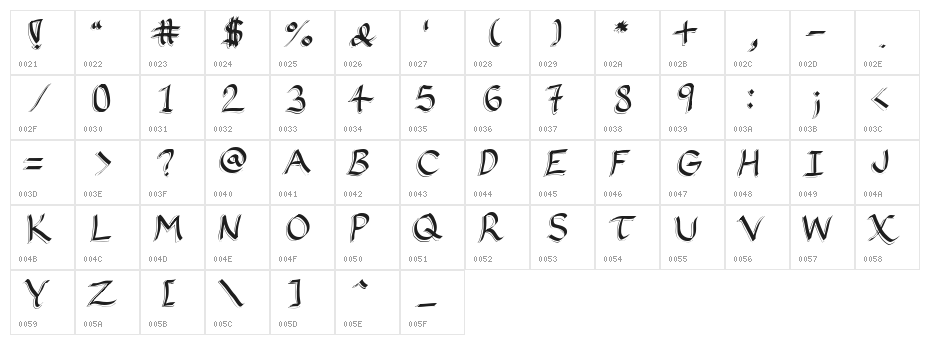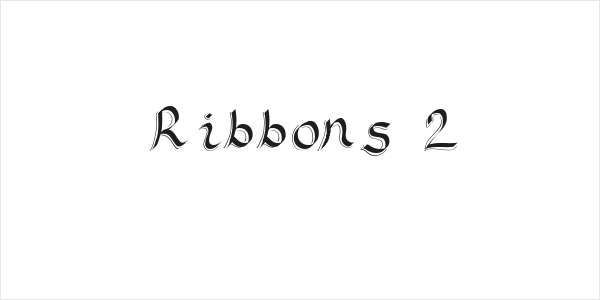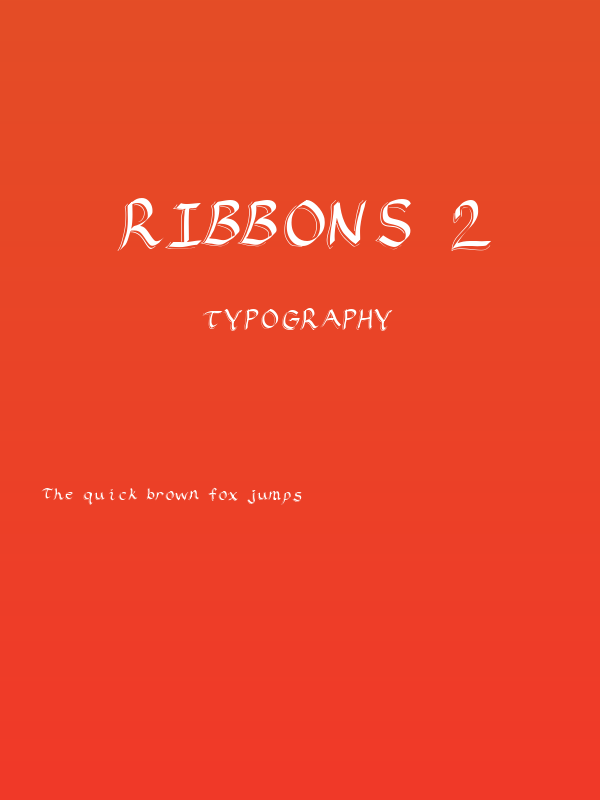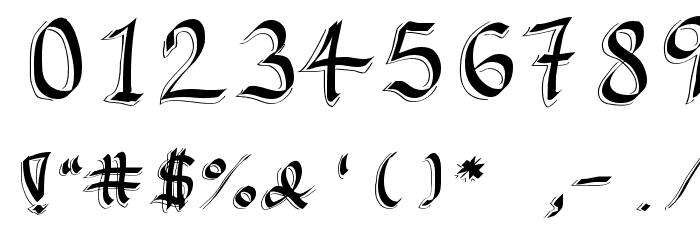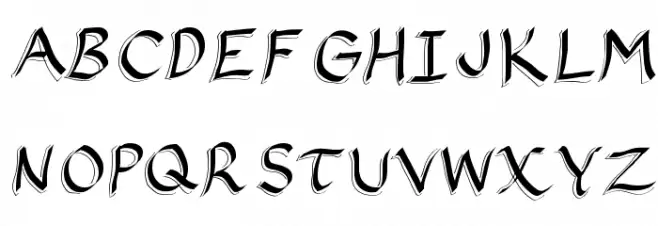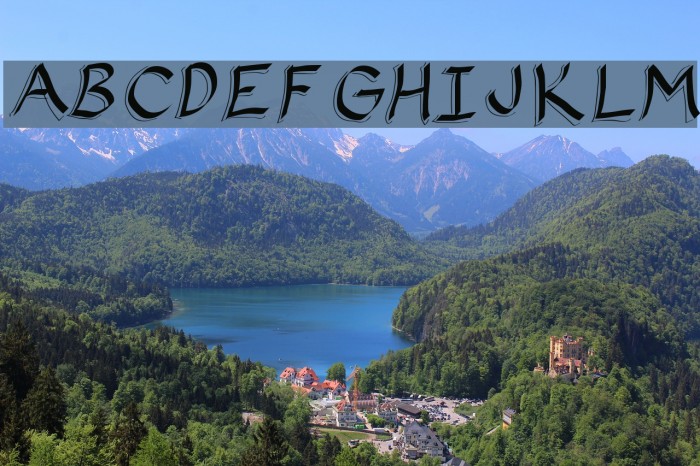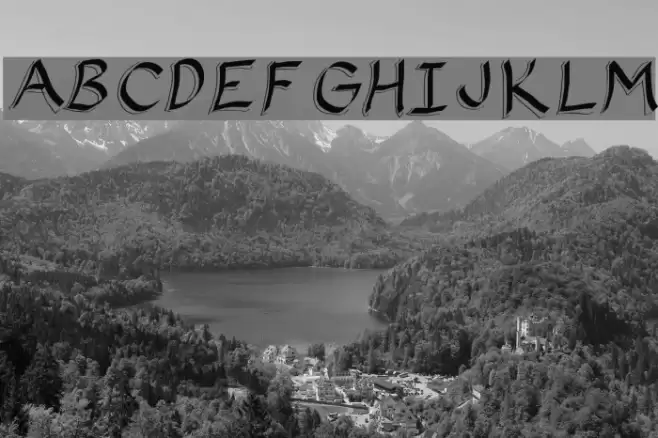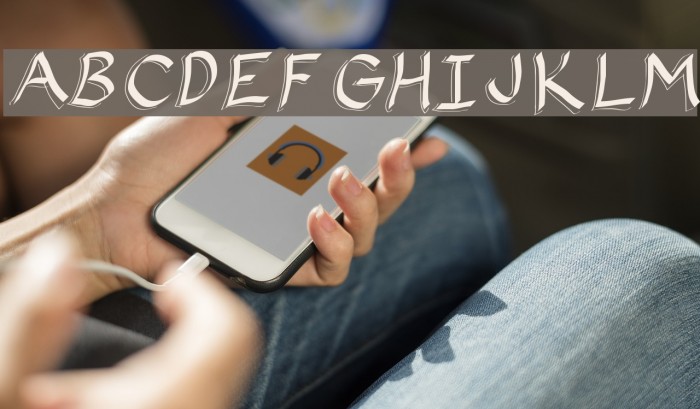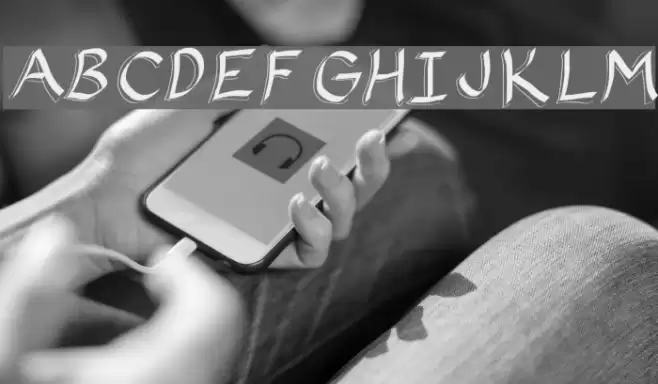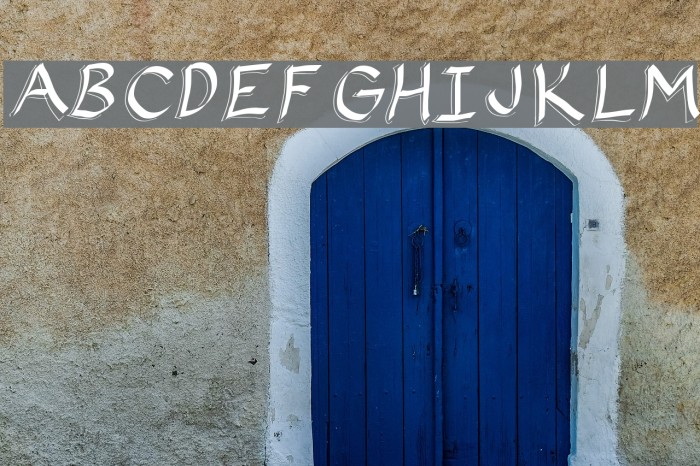
Ribbons 2 Font
| Caso de uso | Logos, Headlines, Artistic projects |
| Proyectos propuestos | Ideal for creative projects such as invitations, branding, and artistic posters where a touch of elegance and uniqueness is desired. |